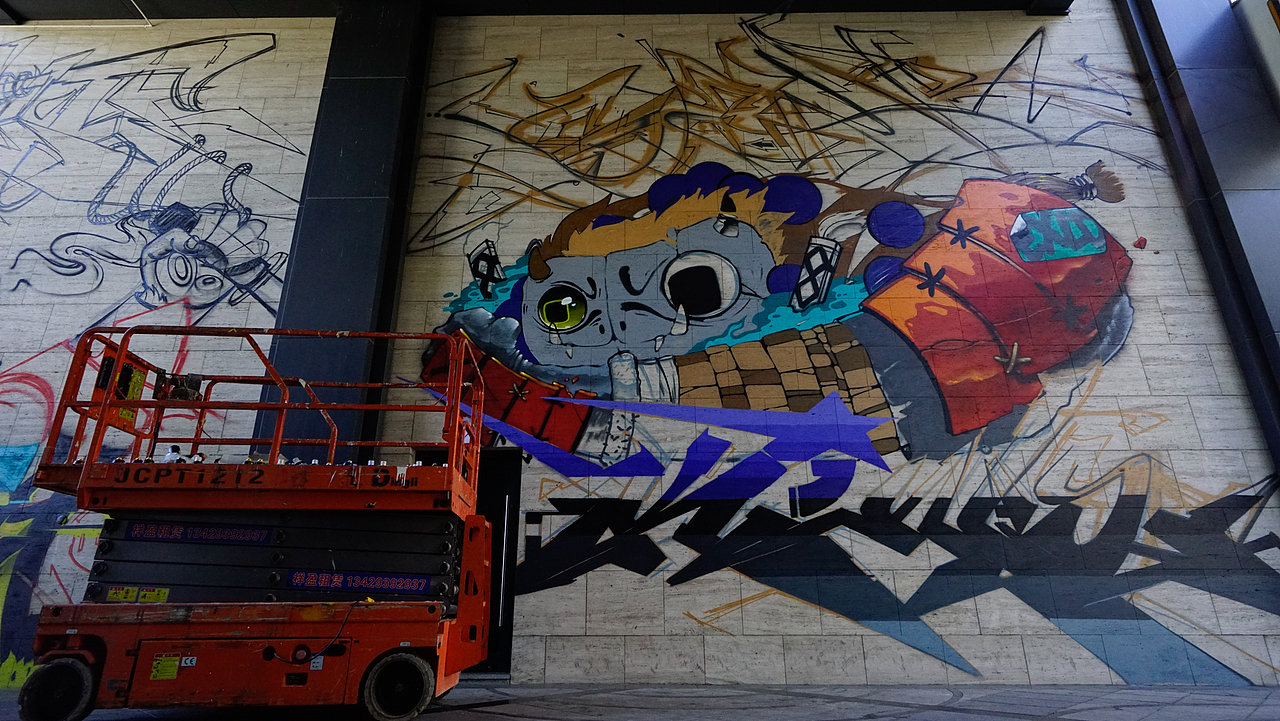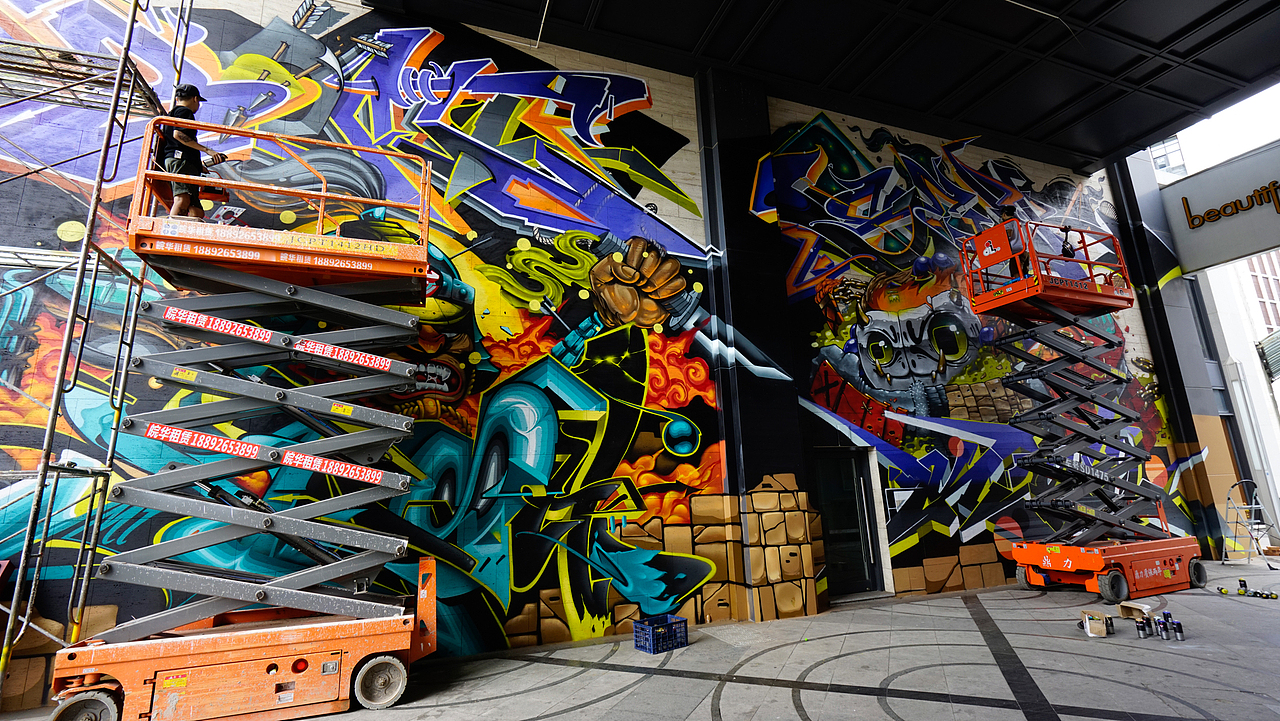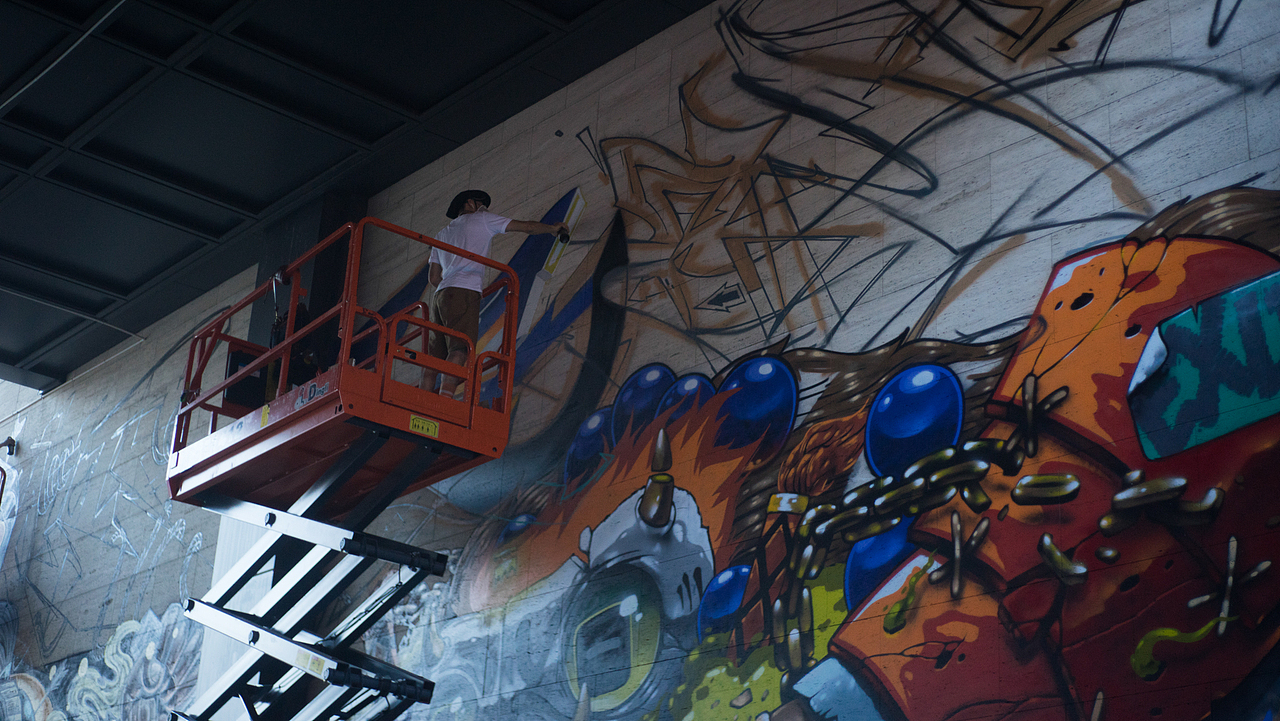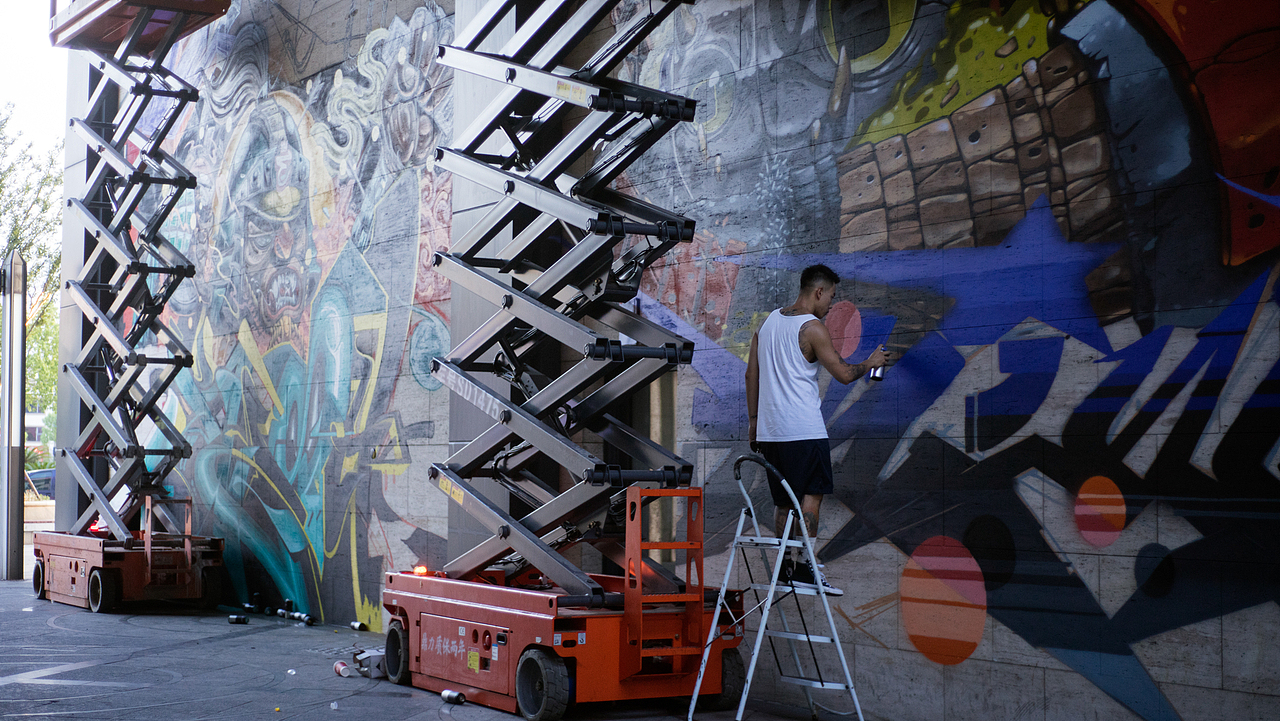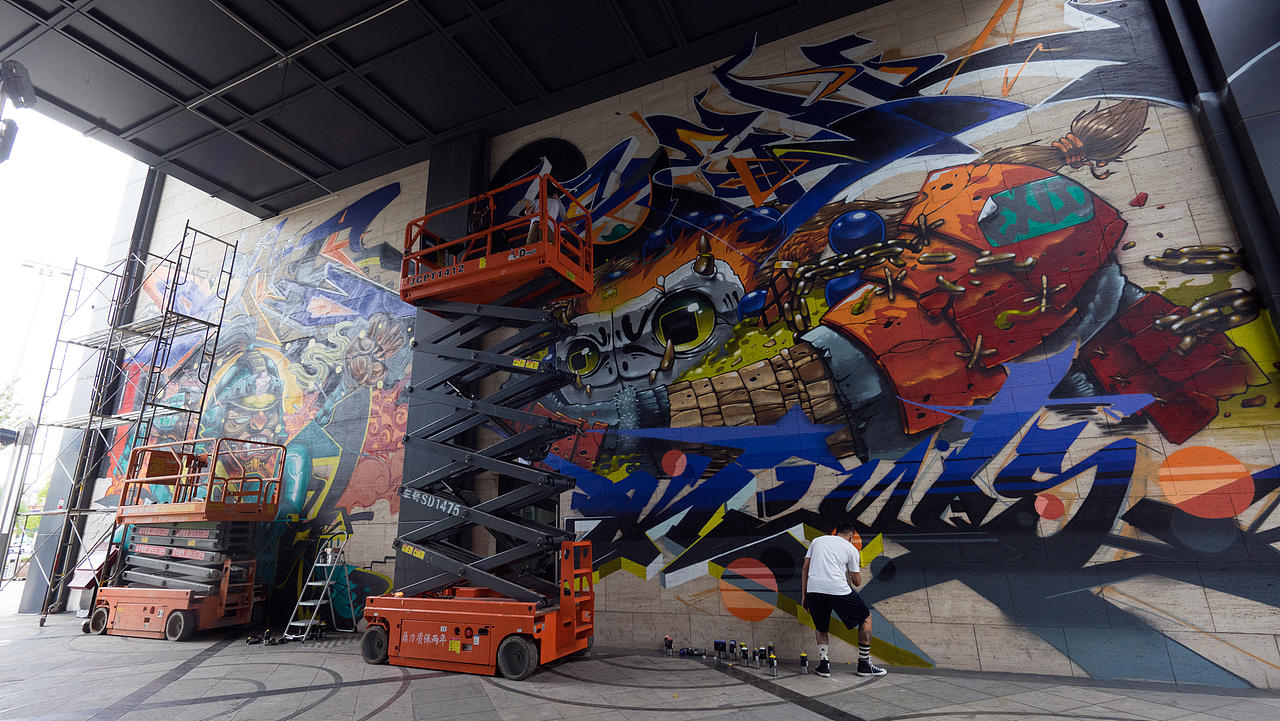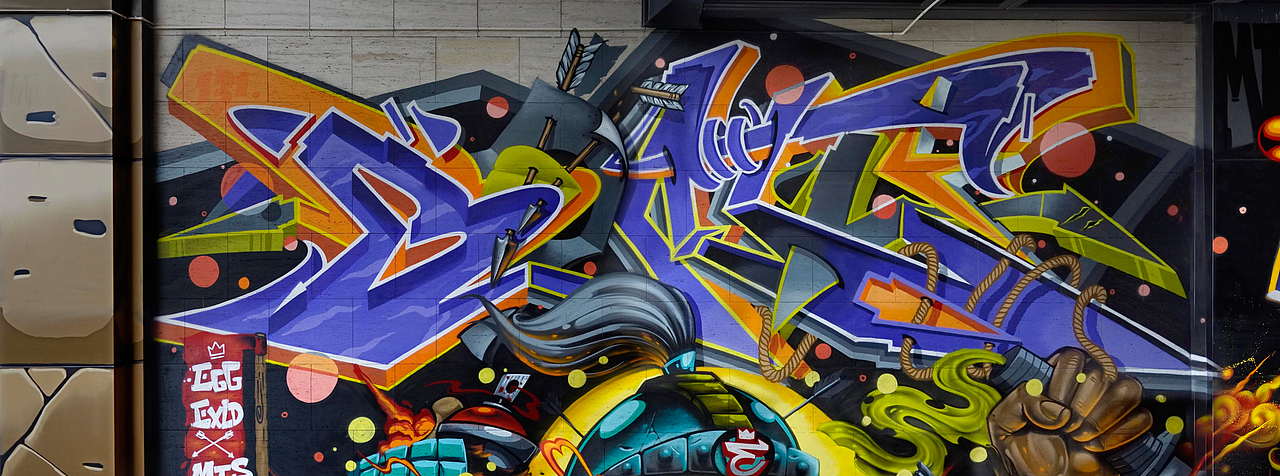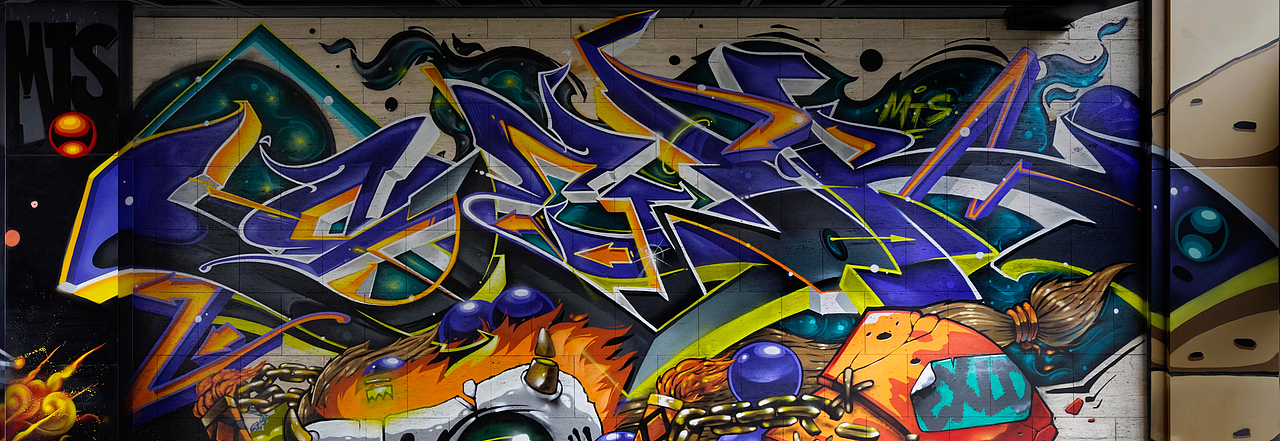
MTS涂鸦-以字体为武器
2017年我们MTS四人在宁波和来自菲律宾的涂鸦艺术家Egg Fiasco和Exld创作的高达10米的画作,每次开始商量怎么画的时候都会说我们这次就休闲画点,最后创作的劲上头后,依然会很强迫症的把所有细节都发挥到极致,左右两边的柱子也在画到一半的时候,灵光闪现地随着主体的完整性改造成了像城墙一样的砖块,两位菲律宾艺术家的代表插画人物形象各带领我们团队的两组字体,字体就是我们人格的代表,简单的英文字母作为载体,承载着我们对形体美感与不同结构矛盾却又统一的理解,用字体笔画和色彩的张力作为武器相互碰撞出灵感的火花也阐述着四个人四种对字体独到的理解。<br>参与艺术家:<br>Bone,Egg Fiasco(菲律宾)、Kish,Senk,Exld(菲律宾),Semik